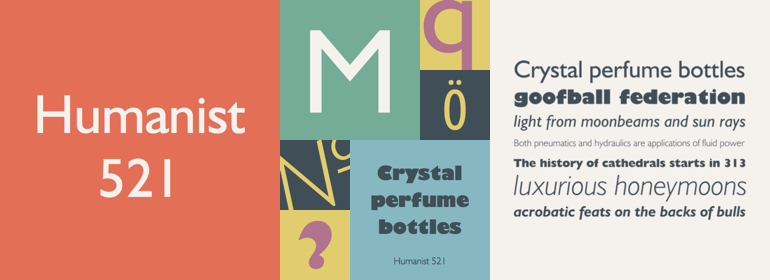
Humanist 521
Humanist 521,这款字体结构工整、笔画清晰,兼顾美观与易读性,适用于标题、正文、海报、包装、LOGO 等多种场景。字形优雅稳定,风格百搭耐看,适配日常排版与创意设计,让文字呈现更舒适、更具质感。Humanist 521一笔一画,皆是细节,以均衡的比例、流畅的线条打造舒适视觉体验,字形端正大气,风格简约现代。无论是商业设计、品牌宣传还是日常排版,都能轻松驾驭,让文字更有格调与力量。Humanist 521字体下载。
字体品牌: Bitstream(Monotype) 设计师:Gill,Eric 字体分类:无衬线体 字体属性:外文 字符集:Unicode 发布时间: 2018